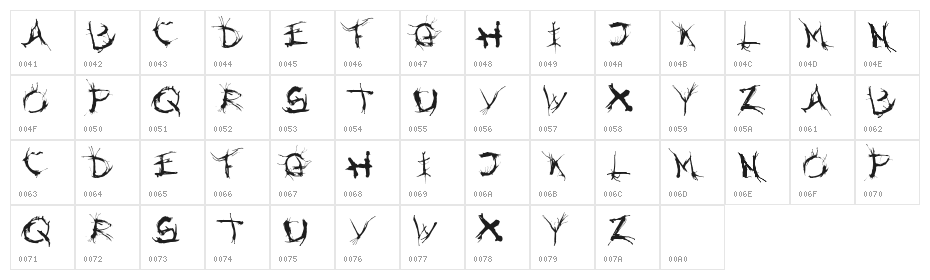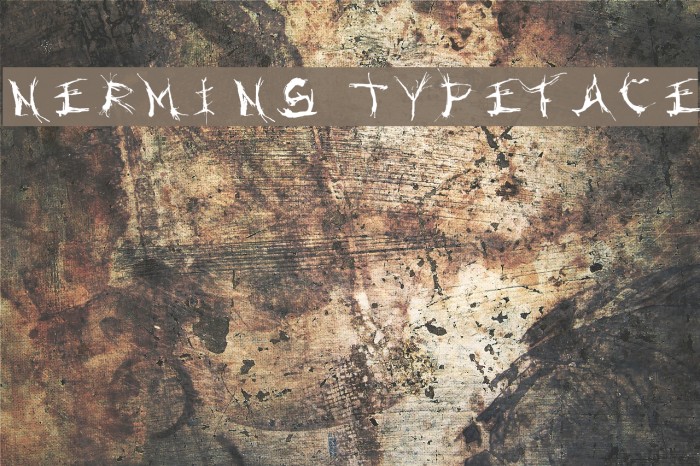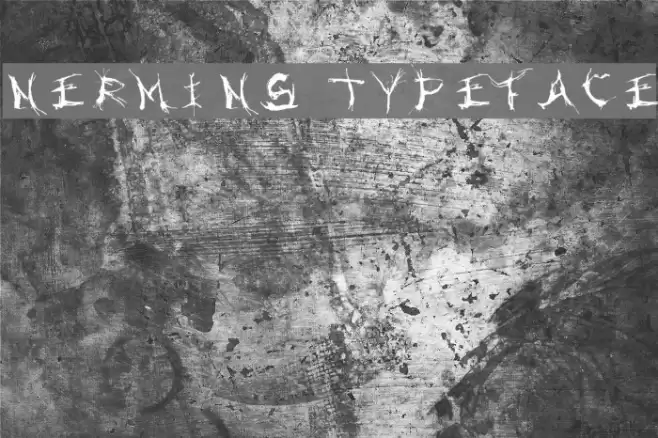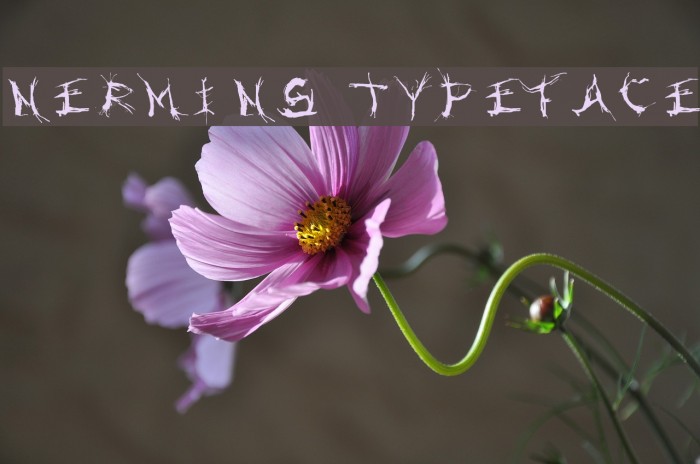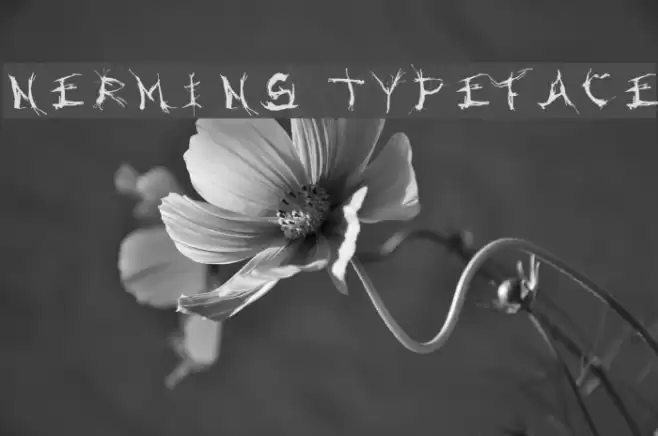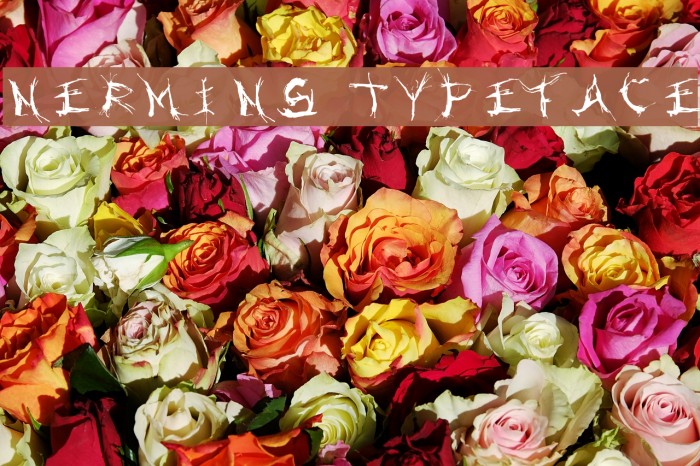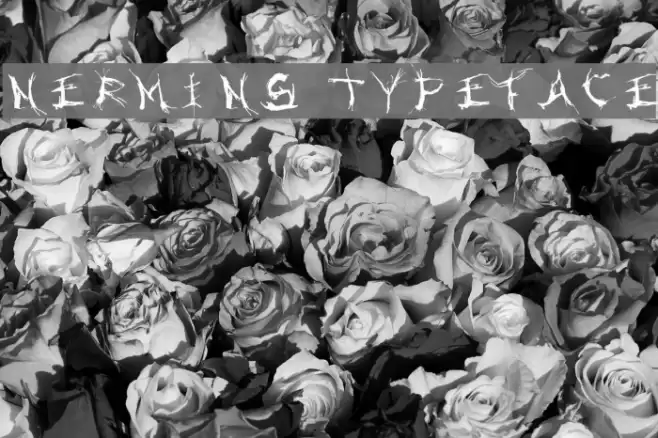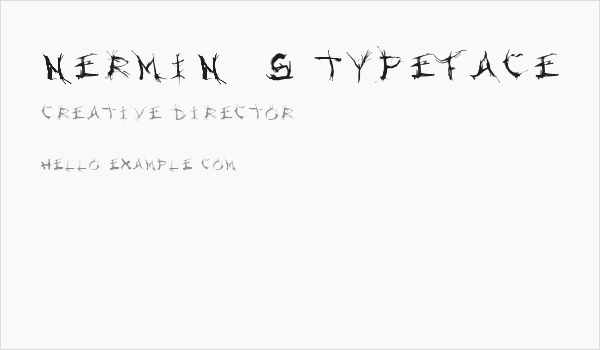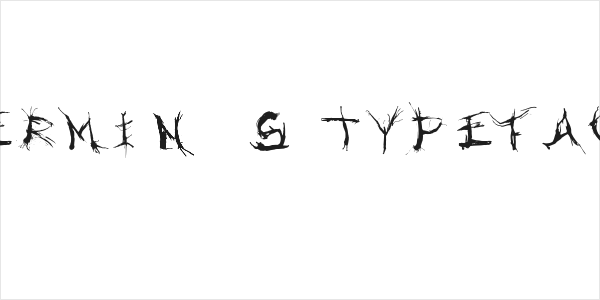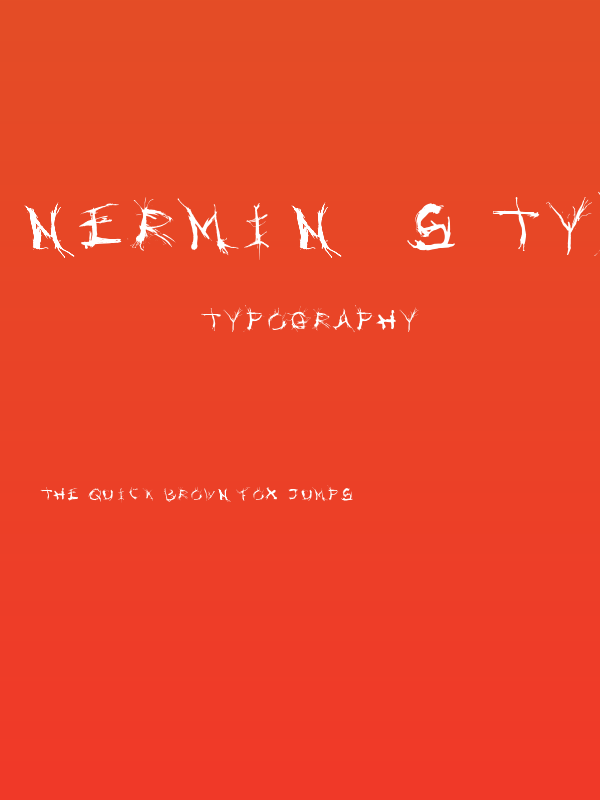
Nermin's Typeface Font
| Anwendungsfall | Logos, Headlines, Artistic projects |
| Vorgeschlagene Projekte | Ideal for nature-themed designs, artistic posters, album covers, and creative branding. |